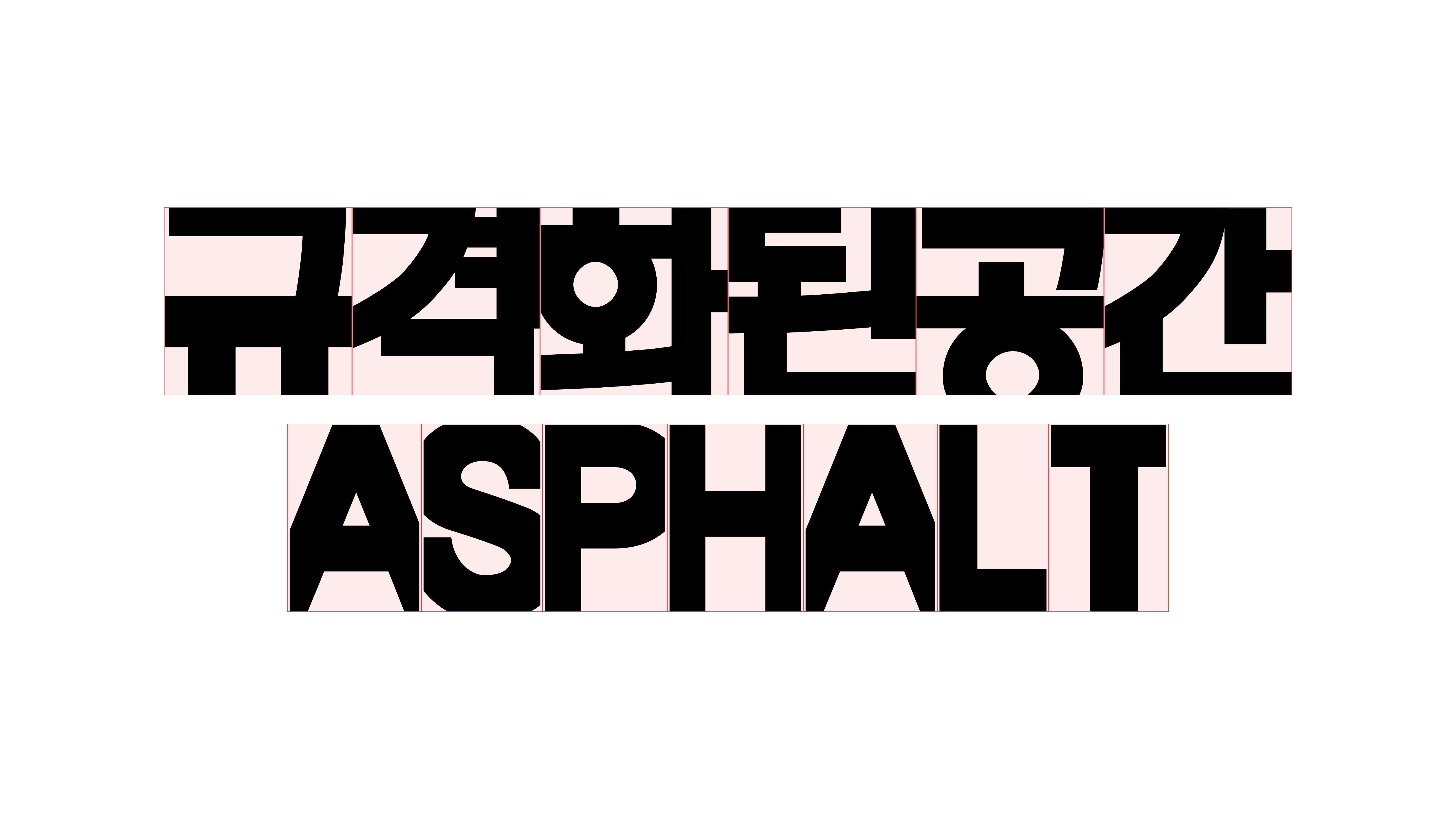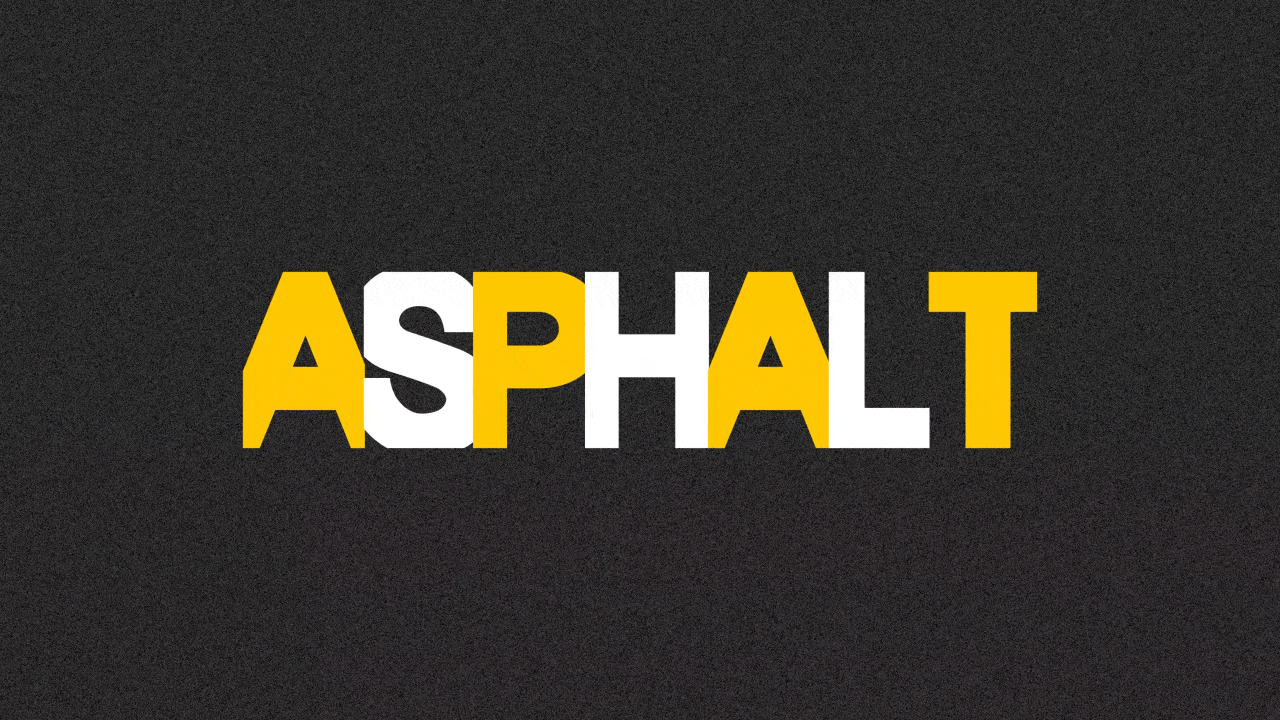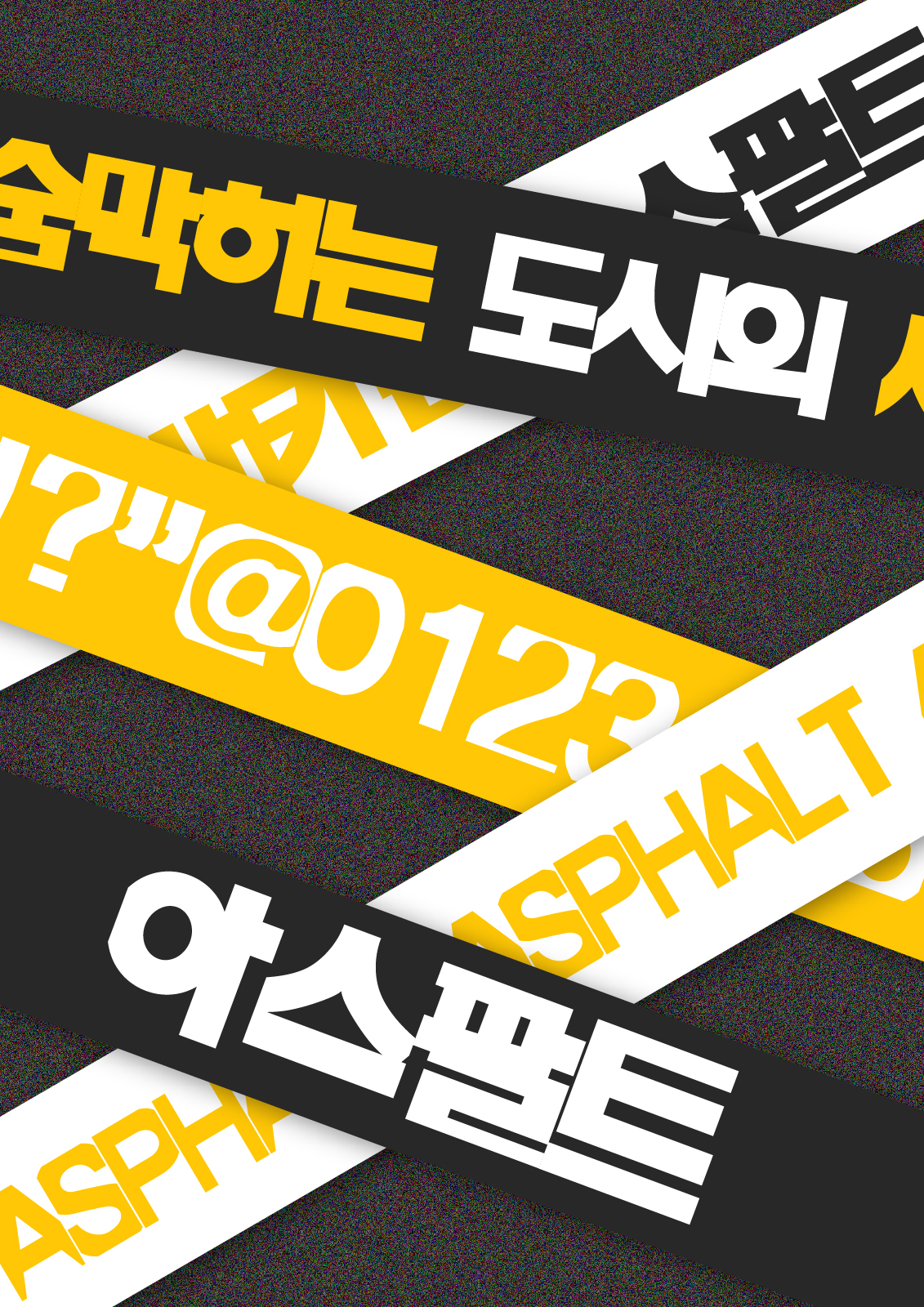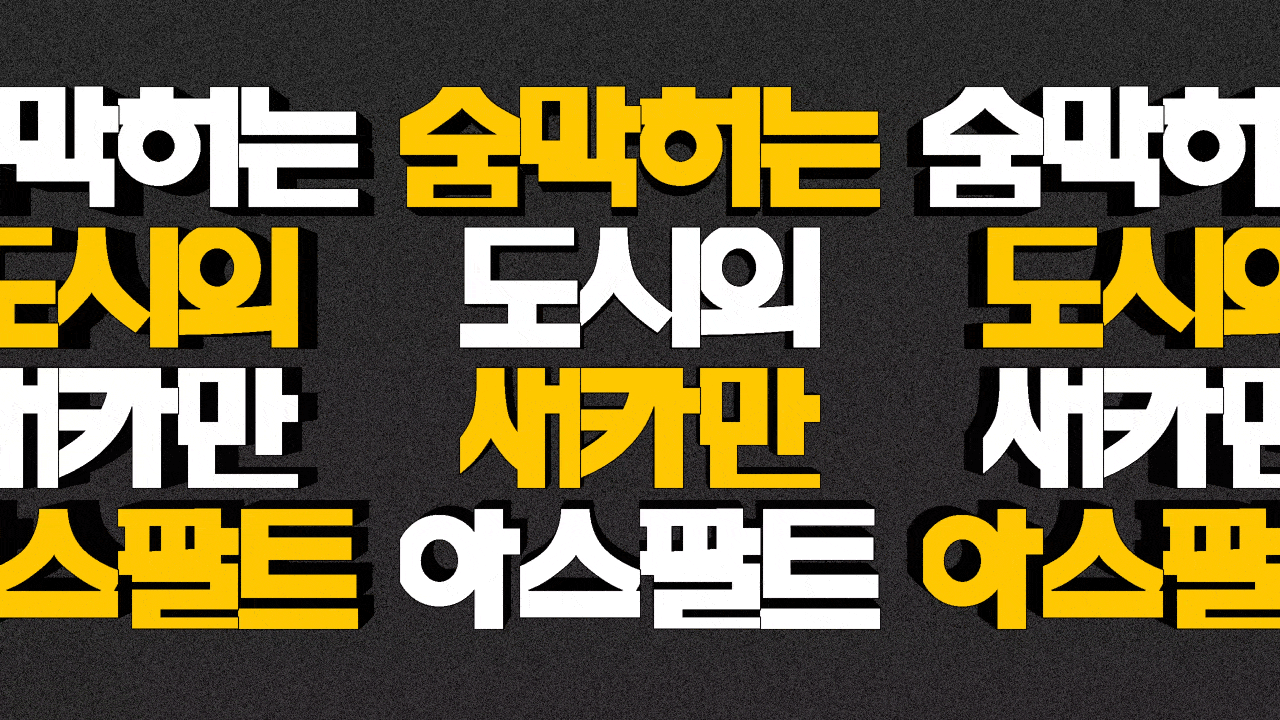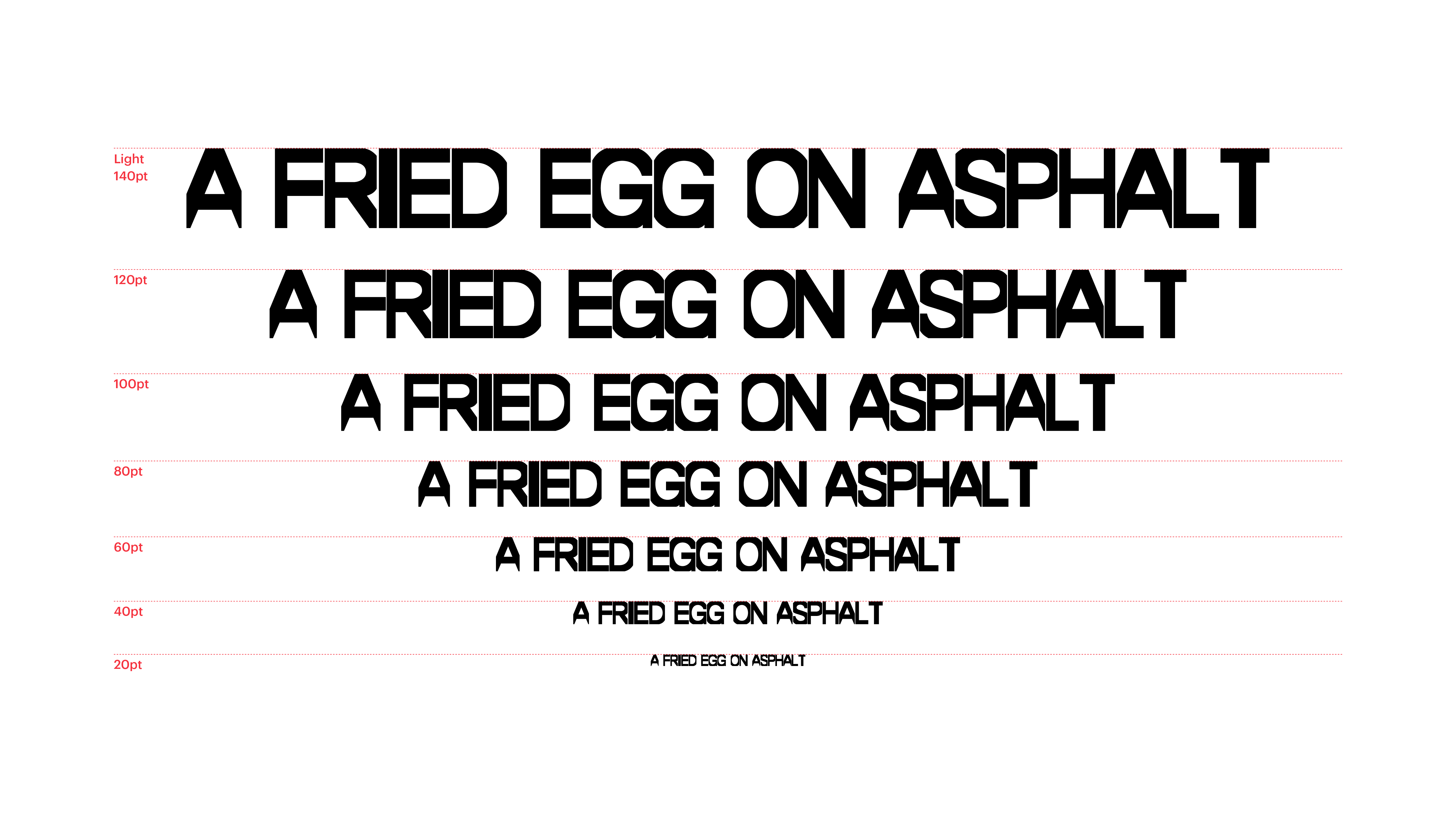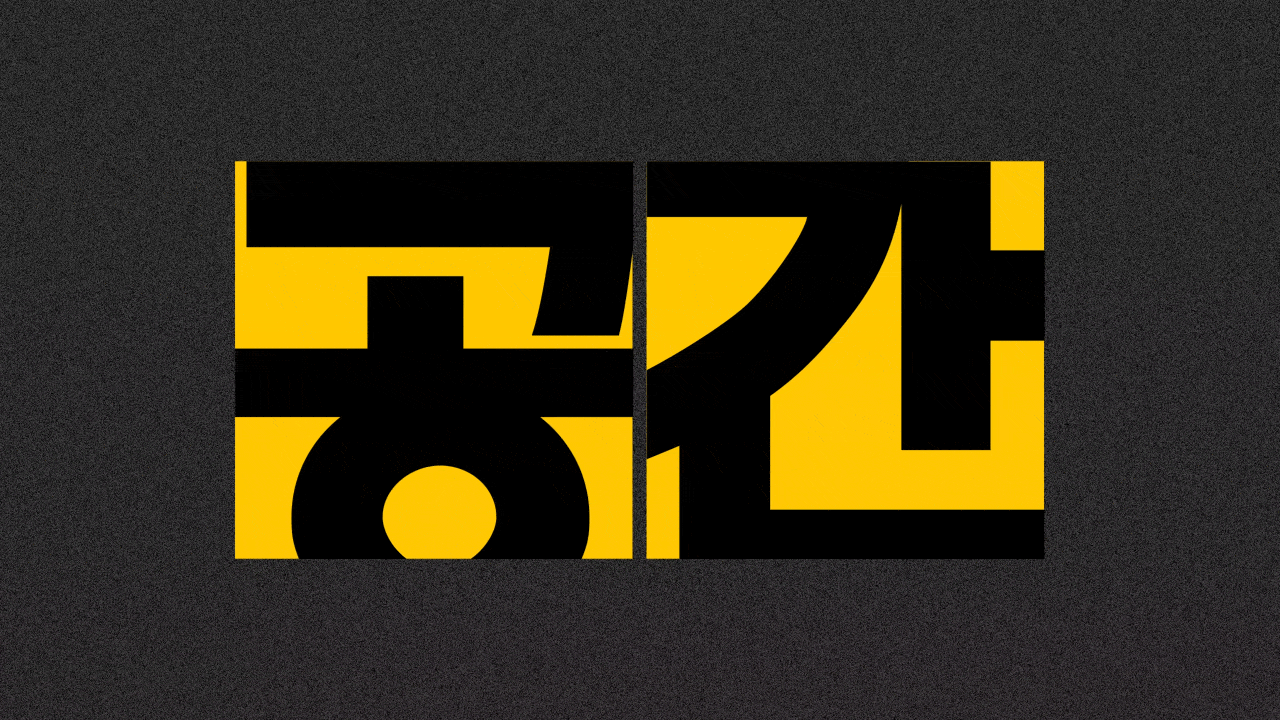
아스팔트
Yoon 아스팔트
도시의 새카만 아스팔트가 떠오르며, 갑자기 답답해지셨다고요? 걱정 마세요, 아스팔트체는 규격화된 공간을 표현하긴 했지만 다른 규칙들에는 제한을 두지 않아, 자유와 해방감을 동시에 느낄 수 있는 폰트니까요. 마치 정장에 운동화를 매치한 날처럼 각기 다른 요소들의 완벽한 조화를 느껴보세요.